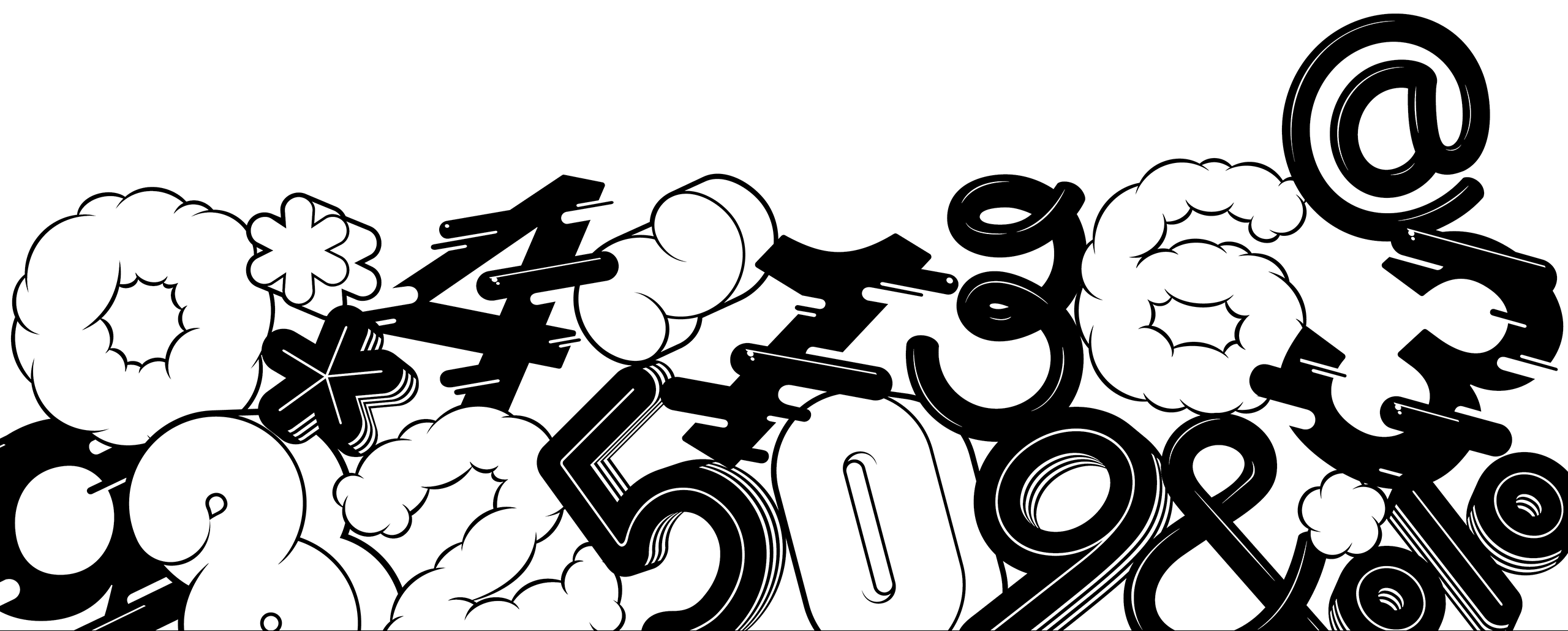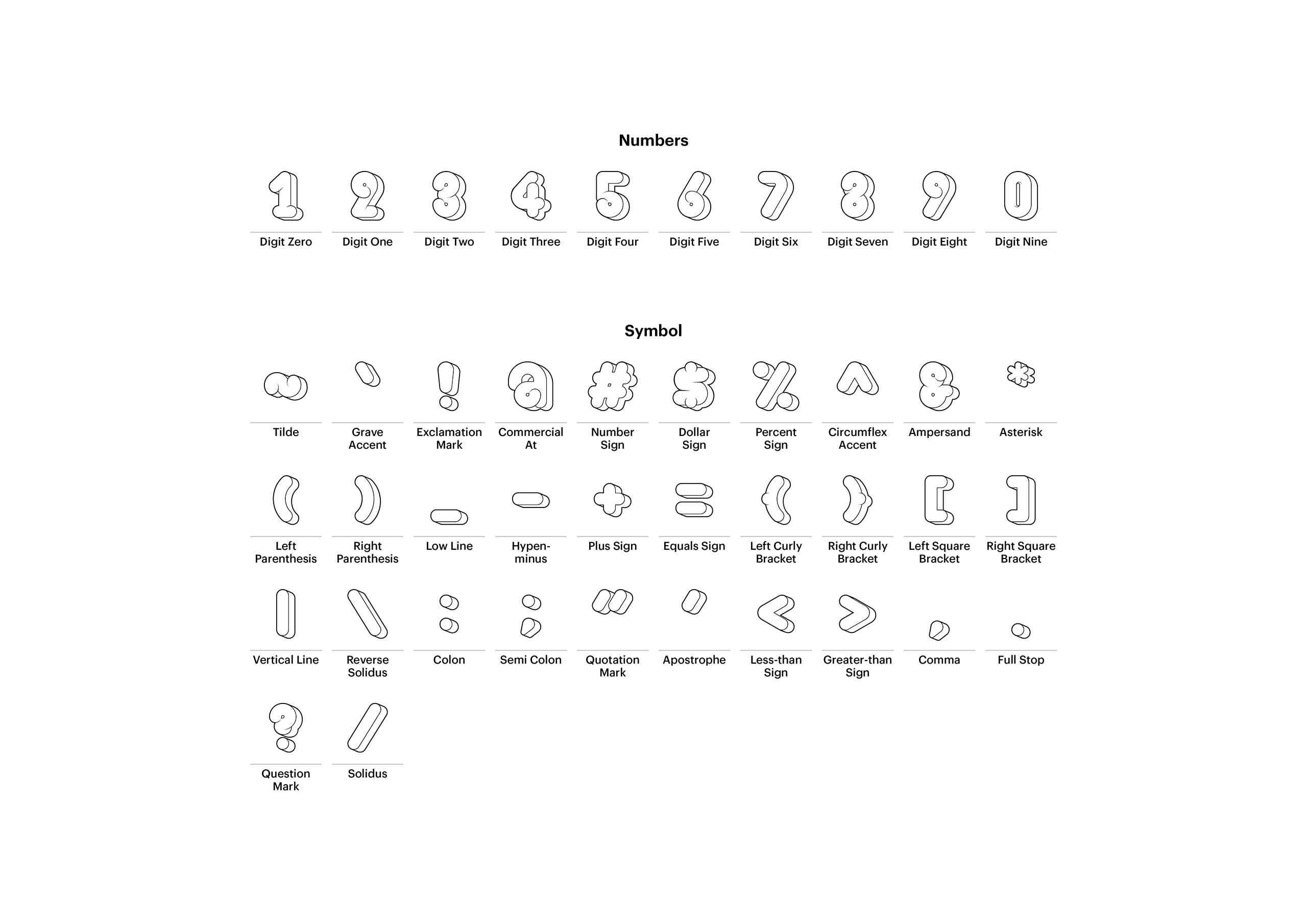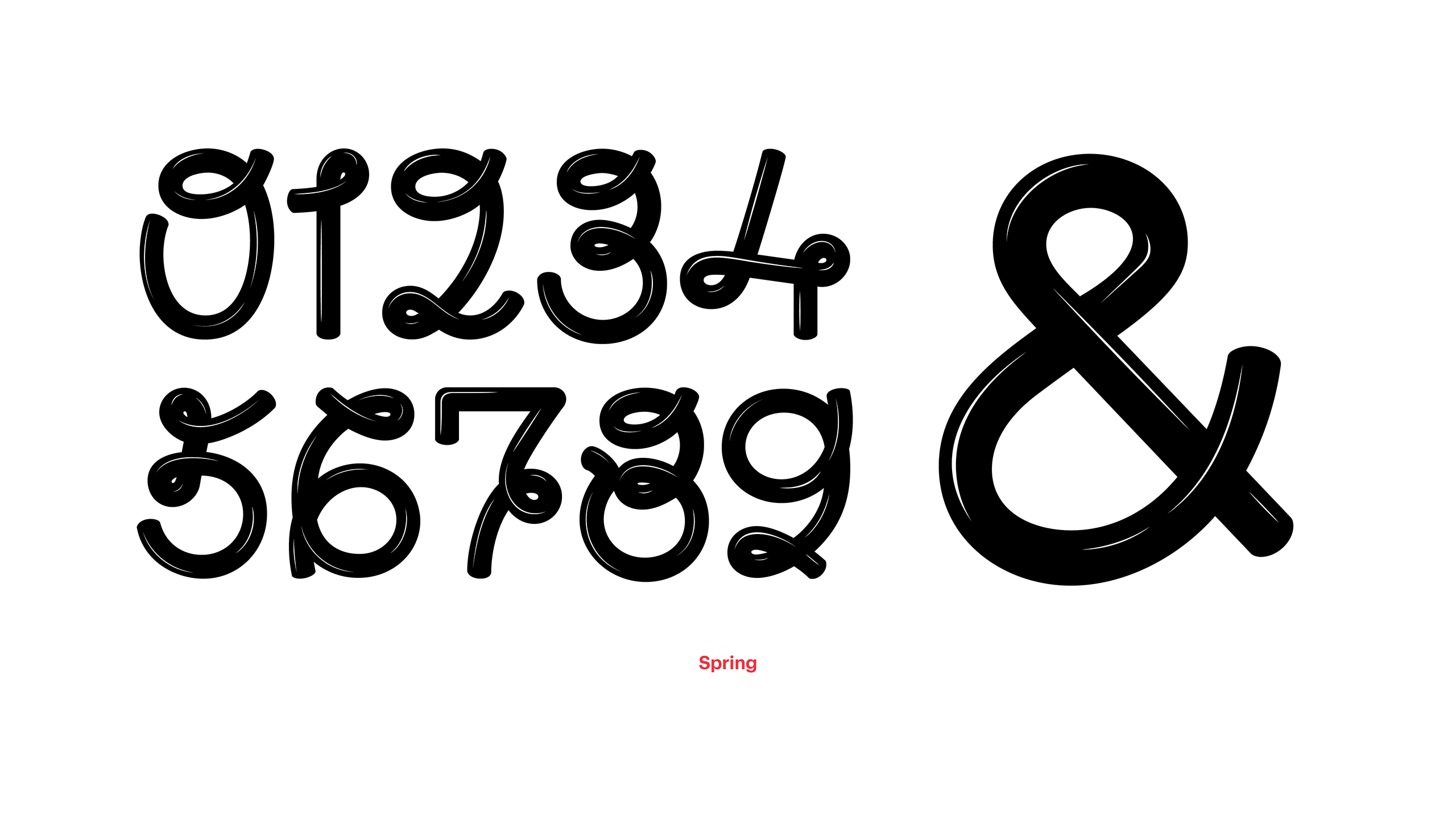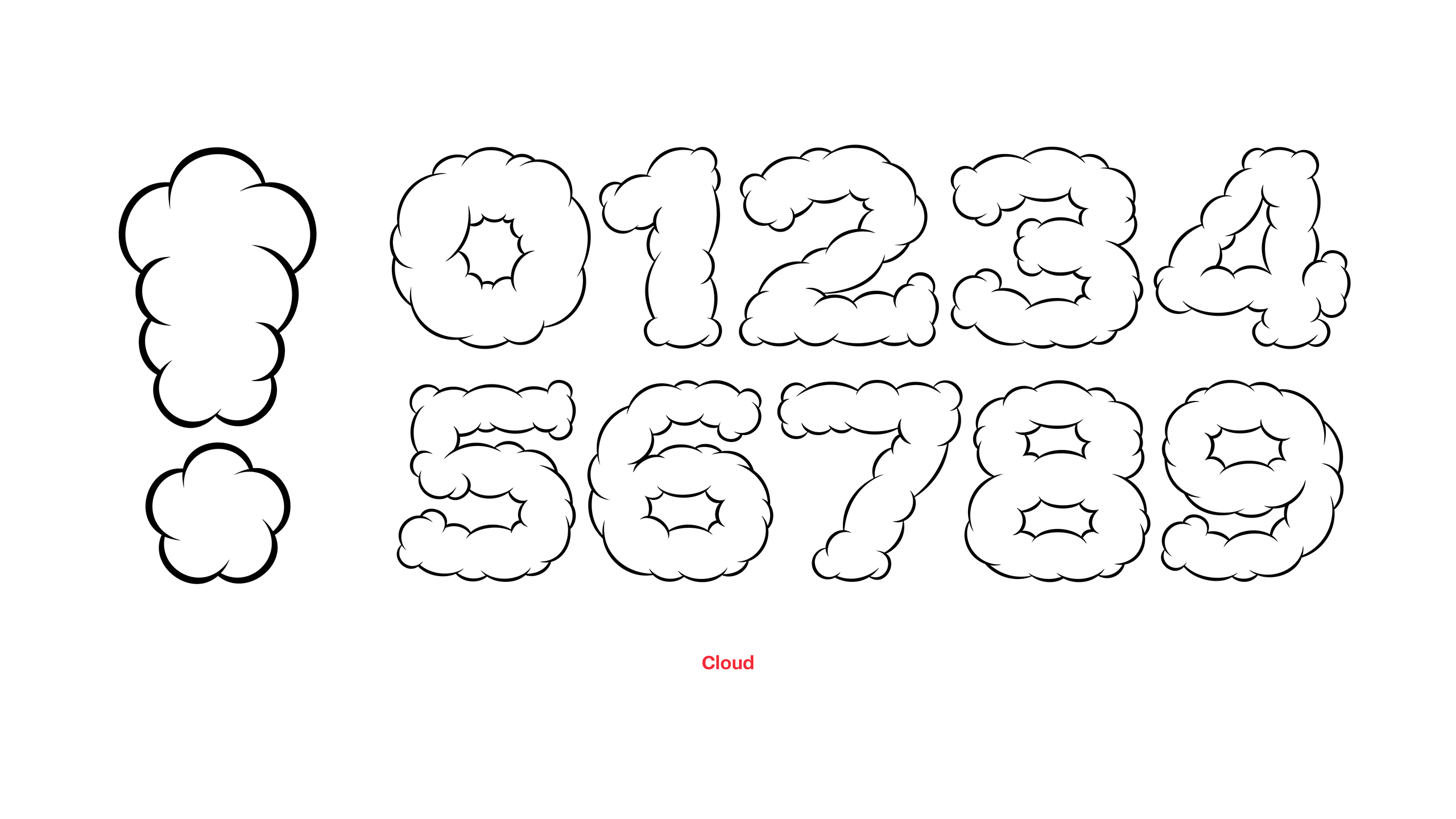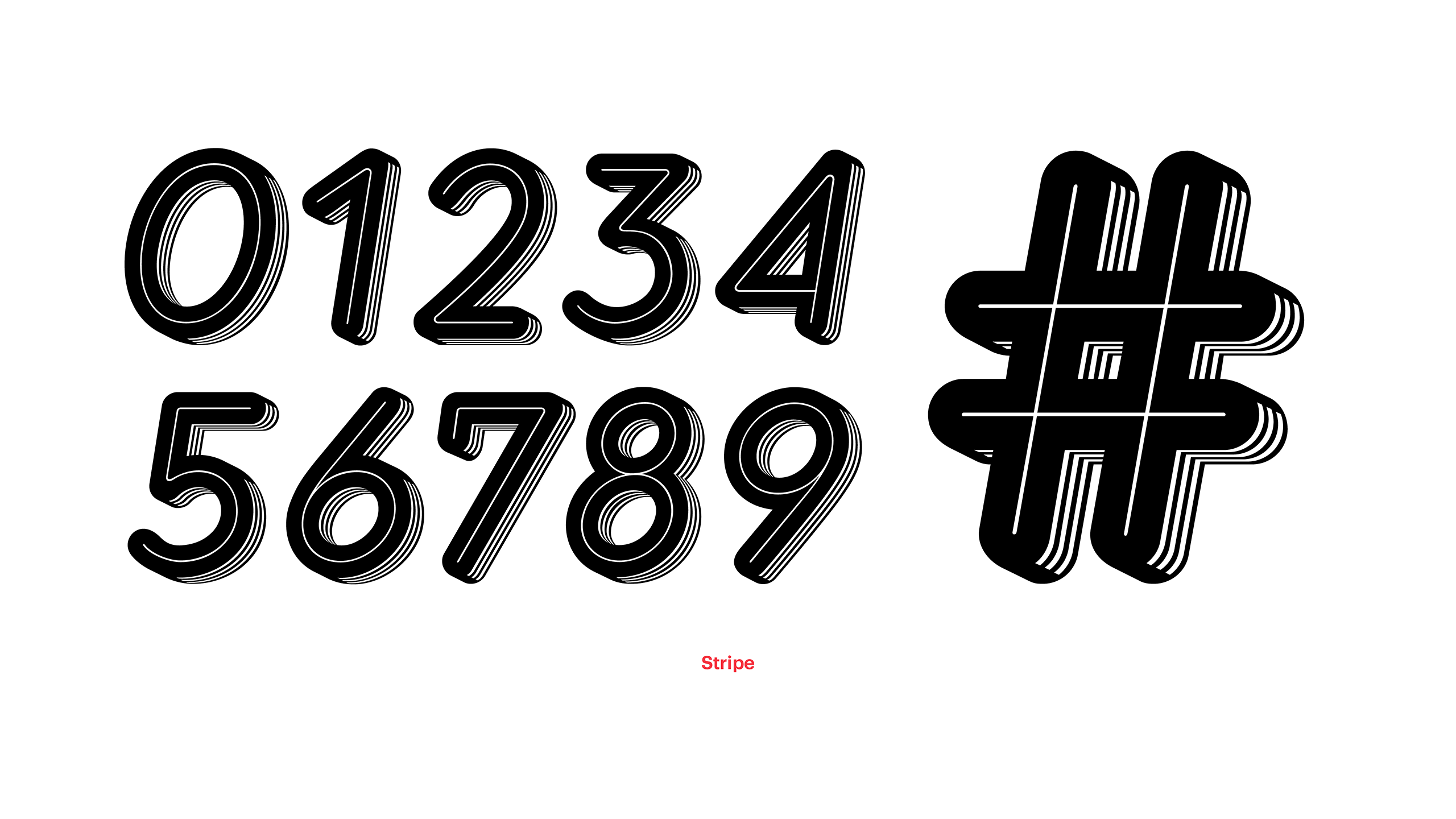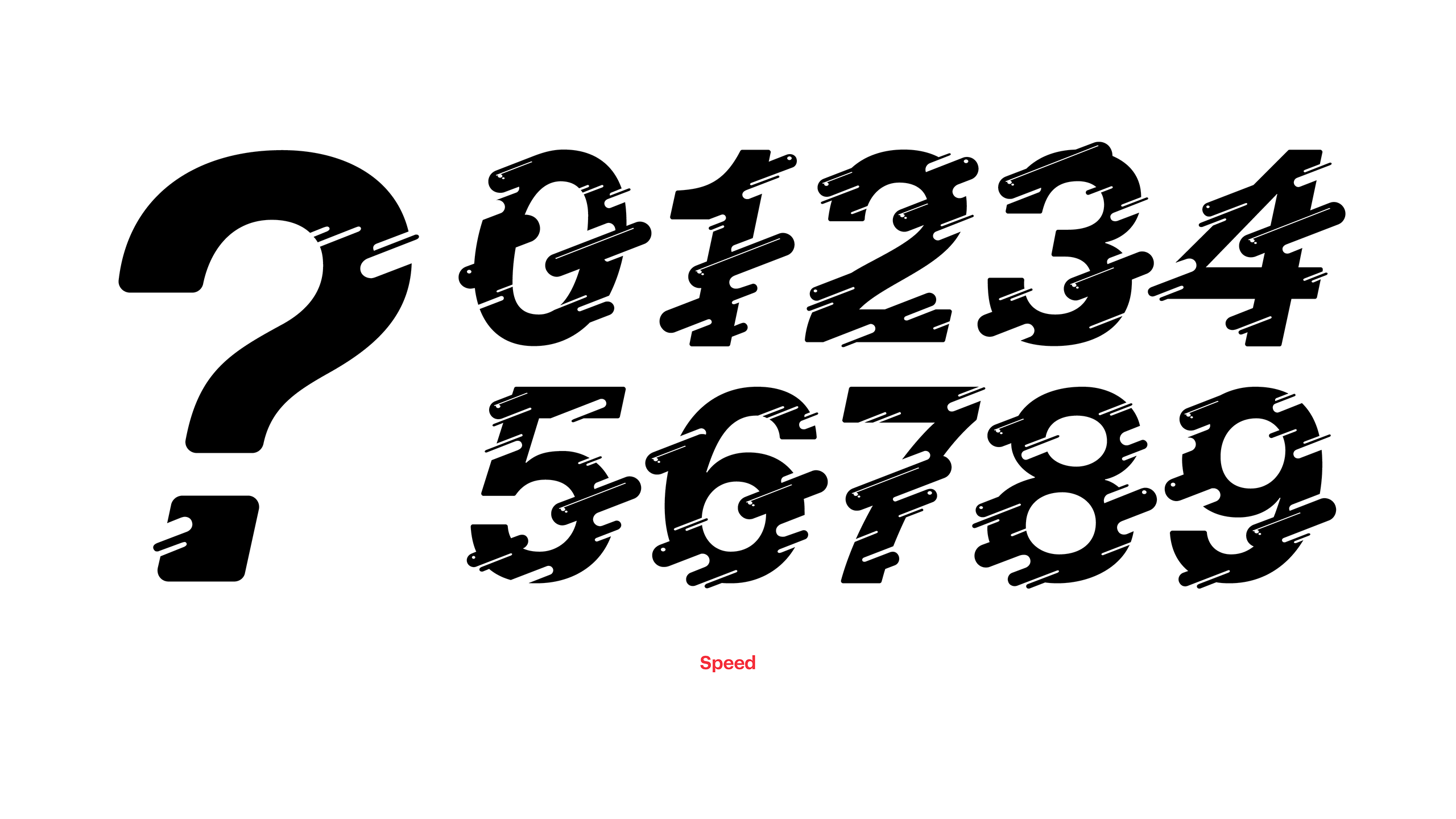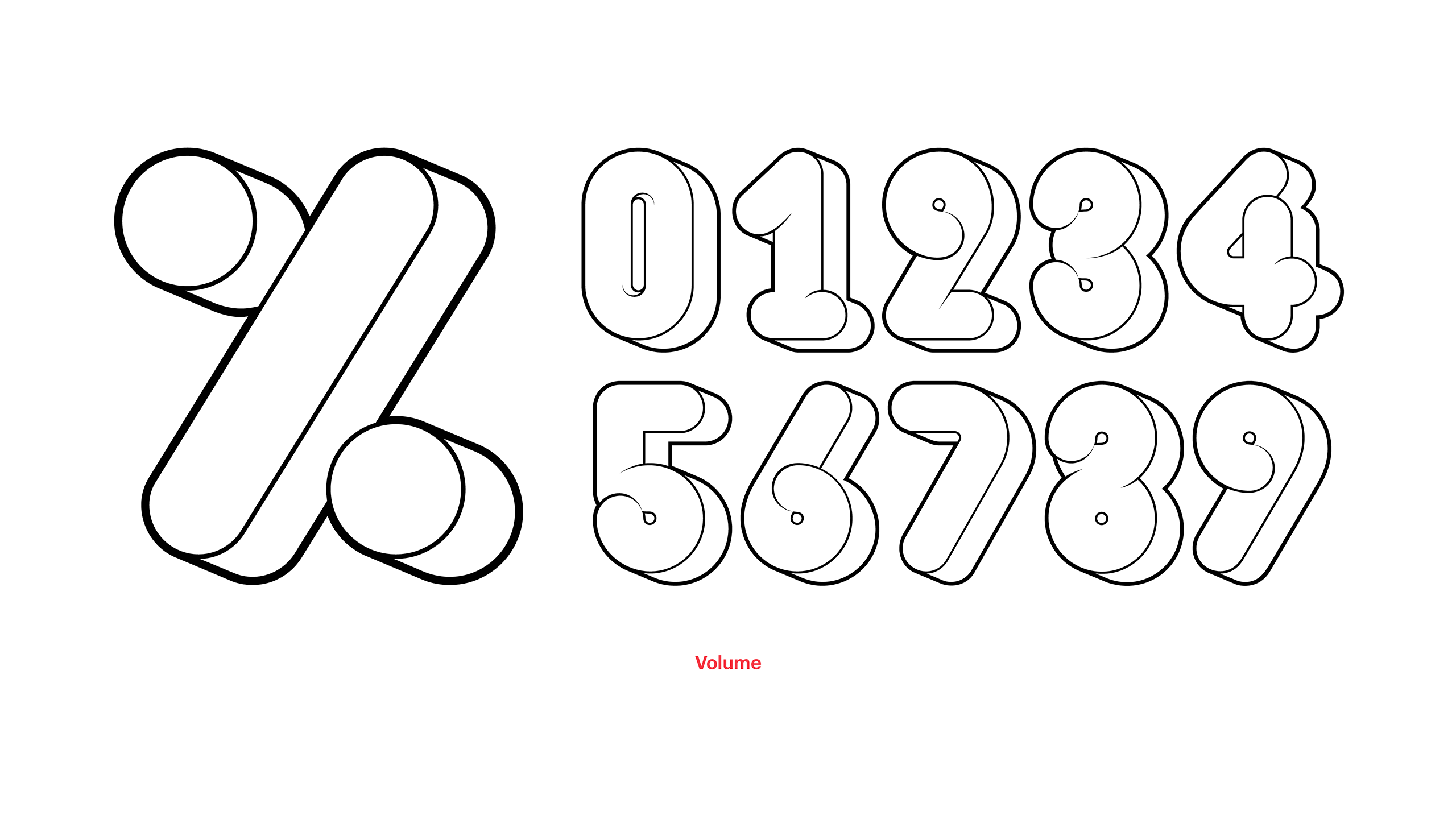
숫자와 기호활자가 주인공인 폰트! 빅빅넘버스는 크게 쓰이는 숫자(10자)와 기호활자(32자)만을 위해 제작된 폰트입니다. 입체적인 볼륨감을 표현한 볼륨, 볼드한 곡선이 특징인 스프링, 구름을 닮은 클라우드, 그래픽적 입체감의 스트라이프, 빠른 속도감을 표현한 스피드. 총 다섯 가지 글자 가족과 함께 커다란 숫자에 나만의 개성을 마음껏 더해 보세요.
포함 문자
숫자 10자 / 기호 32자
“이 구역 주인공은 나야, 나!”두둥실 떠오른 숫자와 기호활자 폰트
숫자와 기호활자가 주인공인 폰트!빅빅넘버스는 크게 쓰이는 숫자(10자)와 기호활자(32자)만을 위해 제작된 폰트입니다.입체적인 볼륨감을 표현한 볼륨, 볼드한 곡선이 특징인 스프링,구름을 닮은 클라우드, 그래픽적 입체감의 스트라이프, 빠른 속도감을 표현한 스피드.총 다섯 가지 글자 가족과 함께 커다란 숫자에 나만의 개성을 마음껏 더해보세요.
빅빅넘버스는 10개의 숫자와 32개의 기호활자로 구성된 폰트입니다.